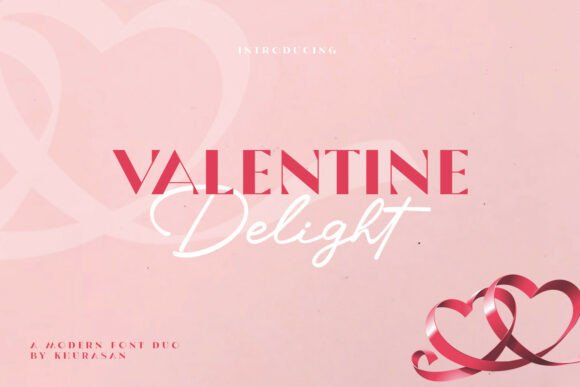
Valentine Delight Duo
Encontrar los elementos de diseño adecuados puede ser un desafío, pero Valentine Delight Duo ofrece una colección excepcional que eleva tu trabajo al instante.
Elaborado con precisión, Valentine Delight Duo proporciona vectores limpios, tipografía suave y una licencia comercial para tu tranquilidad.
Ya sea que estés creando productos POD (impresión bajo demanda), invitaciones de boda o gráficos para redes sociales, Valentine Delight Duo es una opción ideal.